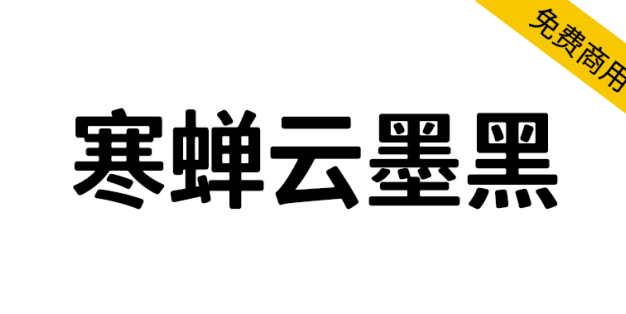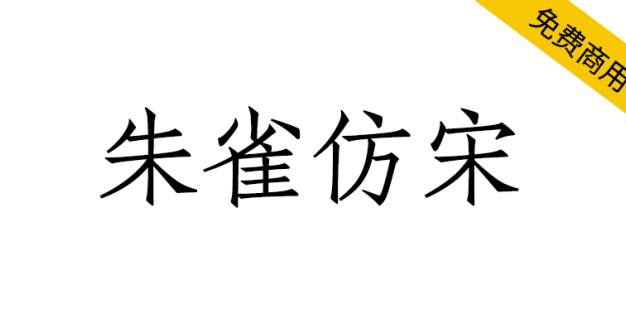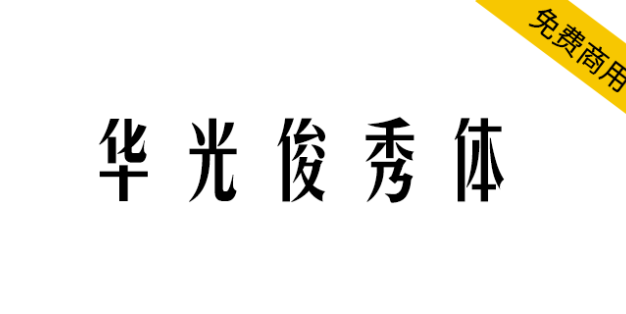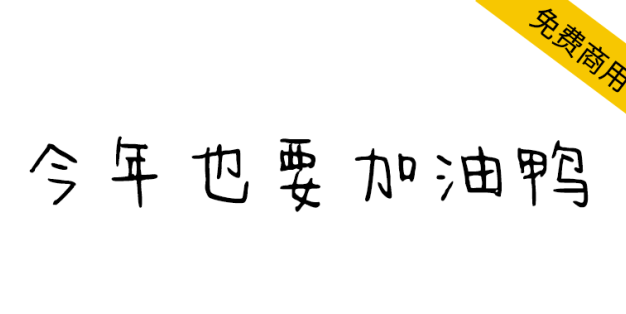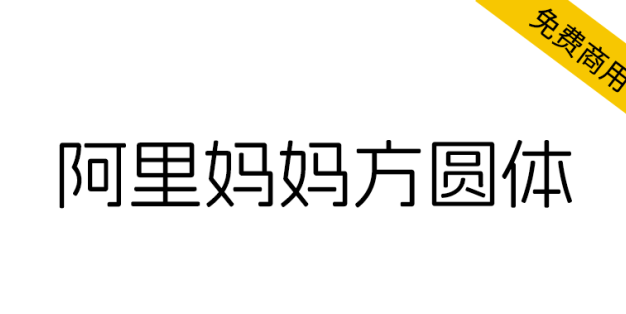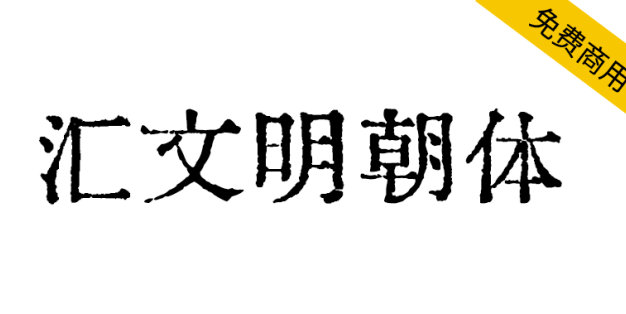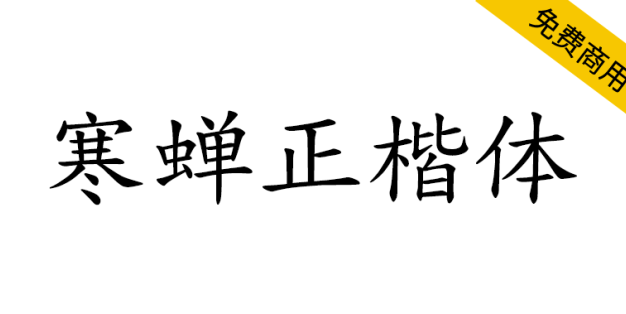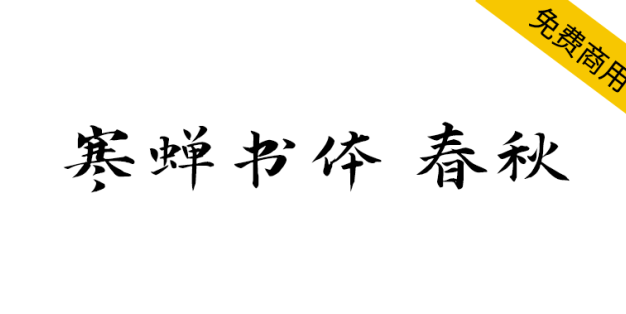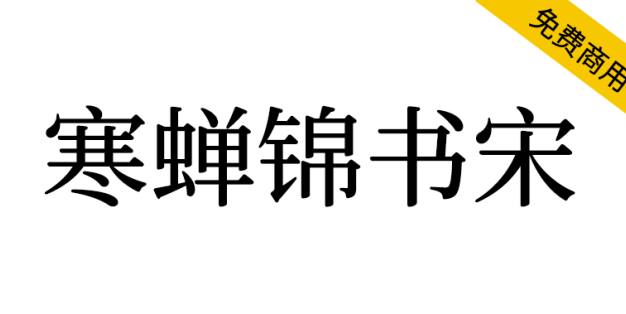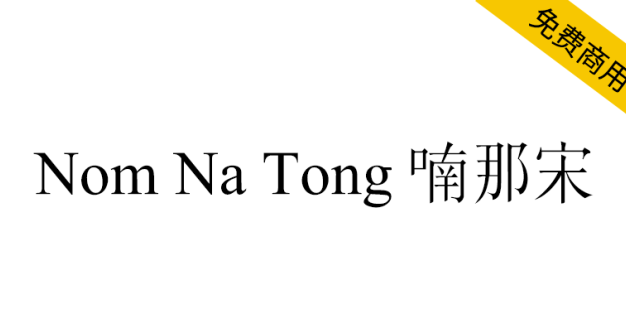
【阿里妈妈东方大楷】还原书法书写韵味,饱满、圆融、浑厚
阿里妈妈东方大楷是基于颜真卿的多宝塔碑算法生成并结合人力完成的一套字库,机器学习到了颜体的丰腴厚重之感,在笔画的描摹上做到了传统书法的收放起伏,规范了骨架、笔画,还原了书法中的落笔、转笔、藏锋、护尾等书写韵味,使整体更饱满、圆融、浑厚。 阿里妈妈东方大楷为中文简体字库,收纳的中文字符包括但不限于GB2312,共计6763个汉字;英文大小写(含全角、半角、合体字等)共105个;常用标点符号共175个…- 0
【阿里巴巴普惠体】面向全社会永久免费商用!
阿里巴巴普惠体是一套全球永久免费正版商用的字体家族,目前涵盖178个语种。阿里巴巴普惠体是一款由中国企业首次发布的可面向全场景使用的免费商用正文字体。以「普惠」之名诞生,阿里巴巴普惠体开放商业授权给所有个人和商家,让更多用户可以免费使用这款字体,以普惠设计助力商业生态增长。 阿里巴巴普惠体3.0为一套符合新国家标准GB18030-2022的简体中文字符集,包含GB18030-2022强制规范三个实…- 0
【乡立方黑体】以字为媒,绘乡村风情,传品牌温度
我是乡立方黑体,由火石品牌字体团队为乡立方量身定制,以字为媒,绘乡村风情,传品牌温度。 乡立方字体设计团队秉承服务大众的原则,致力于打造一款既实用又广泛适用的字体,希望它能被广泛应用于各行各业,真正做到字体好用,适用面广,实现字体使用便捷、应用场景丰富多样,无论在哪种传播媒介中都能展现出卓越的效果。 乡立方黑体总共囊括了4500个基础常用字,可覆盖日常98%的使用范围,未来,我们将根据实际情况逐步…- 1
【阿里妈妈方圆体】目前国内外为数不多的中文双轴可变字体
阿里妈妈方圆体为一款简体中文双轴可变字体,收纳的中文字符包括但不限于GB2312,共计6763个汉字;英文大小写共52个;常用标点符号共227个,总计7042个字符 设计说明:通过智能 AI 的方式在20天内完成的这款字,是目前国内外为数不多的中文双轴可变字体。方体坚实而硬朗,圆体润泽而柔美;方圆间的切换让方圆体极具适用性,也解放了创意表达的更多可能性。粗细的可变使得设计师具备无限微调的可能,让创…- 0
【胡晓波男神体】永久免费商业使用
【寒蝉书体 春秋】基于“演示春风楷、演示秋鸿楷”的拓展字形
寒蝉书体_春秋是基于开源字体“演示春风楷、演示秋鸿楷”的拓展字形 春风 更新提要 调整西文字符及数字大小更加均衡。 调整部分字符忽高忽低的问题。 调整西文字偶距,优化横向排版。 优化竖向排版。 新增 啰 瞭 舖 三字补全一级规范通用字。 新设计的.notdef,补充一些标点符号。 秋鸿 更新提要 调整西文字符及数字大小更加均衡,去除连笔和文字风格更接近,调整粗细。 调整部分字符忽高忽低的问题。 调…- 0
【思源宋体】思源宋体字体下载,免费商用
思源宋体(Source Han Serif)是Adobe 与 Google 合作开发的最新泛 CJK 字体,它是对应于思源黑体的宋体字体。思源宋体与思源黑体这两种字体是为了响应统一设计的需求,以服务于东亚 15 亿人口。 思源宋体支持四种不同的东亚语言(简体中文、繁体中文、日语和朝鲜语),该字体还包含多个西方字形,支持拉丁语、希腊语和西里尔文脚本,这些字形均来源于 Source Serif。思源宋…- 0
【寒蝉正楷体】一个为优化中西文排版的楷体项目
寒蝉正楷体(Chillkai)是一个为优化中西文排版的楷体项目,由中文字体《全字库正楷体》和西文字体《Gentium》重新整合优化。 全字库正楷体字符非常丰富,还有多语言的支持,成为楷体的优秀范本。但西文部分和中文部分不是特别融合。竖排比横排文字排版更好,个人使用感受。 西文部分Gentium是个人最喜欢的西文字体之一,是我认为和楷体搭配最好的西文字体。无论是与文鼎U楷或者其他楷体,整体比原字体西…- 0
【汇文明朝体】一款比较原滋原味的旧铅字印刷风格字体
本字体制作始于2019年1月份,因一切开始于是我扫描《文汇报》上面的《汉字简化方案草案》,后来又收集、扫描了各种历史文献资料,汇总挑选而形成了这样一款字体,故名「汇文明朝体」。 本字体的字形来源主体为五六十年代官方各种汉字改革文件,简体字部分基本复原汉字简化后、字形改造前的书籍印刷体样貌。繁体字、传承字部分基本还原民国至共和国初期字形样貌,是比较原滋原味的旧铅字印刷风格。 收录范围及规则 全覆盖大…- 0
【字体圈欣意吉祥宋】一种圆润纤细古风女性化的字体
整套字形视觉感偏瘦高,宽高比例为4:5,尝试过1:1甚至更矮的比例,不够优雅,因为像这种圆润纤细古风女性化的字体,都是比较修长才好看,最后才决定4:5这个近乎完美的比例。这款字风格圆润,比如横画开头及结尾由传统字体的三角尖凸变成较圆润的风格,竖画由三角尖凸也变成圆润无尖凸风格,竖勾撇捺点的笔画同理2021,祝您吉祥! 这套字涵盖国家GB2312编码标准的6763个中文字符,52个英文字符,10个阿…- 0
【鸿蒙 HarmonyOS Sans】一款多语言的无级可变字体
华为鸿蒙字体 (HarmonyOS Sans),华为定制字体,为鸿蒙OS一同上线,于2021年6月发布上线,可以免费商用。设计上聚焦于功能性、普适性,是一款多语言的无级可变字体,该字体支持简体中文、繁体中文、拉丁、西里尔、希腊、阿拉伯等5大书写系统,105种语言全球化覆盖。 通过研究用户在不同场景下对多终端设备的阅读反馈,综合考量不同设备的尺寸、使用场景等因素,同时也考虑用户使用设备时因视距、视角…- 0
【韩契在民体 한글재민체】基于韩国古文字的字体设计
韩契在民体(韩文名:한글재민체,英文名:hangeul jaemin)是以1908年颁布的《大韩国会开幕原则书》(国家注册文化财第449号)中的毛笔书法字体为基础,由朴载甲前首尔大学医学院教授和金敏国民大学技术设计专门大学院院长共同开发。2020年在韩文字日发布了韩契在民体1.0,2021年增加了KS标准汉字的韩契在民体2.0,2022年又增加了韩国独有的203个汉字和大法院人名用8289个汉字等…- 0
【寒蝉云墨黑】基于思源黑体,添加圆角,更加温润的黑体
基于思源黑体(SourceHanSansSC) 修改,添加圆角,更加温润的黑体。排版细节优化,重构字重比例。 字体风格 使用许可 本字体以SIL Open Font License 1.1(SIL 开源字型授权版本1.1,简称SIL OFL 或OFL)授权协议发布,这个授权的自由度非常高: ✔ 这款字体无论是个人还是企业都可以自由免费商用,也无需知会或者标明原作者。 ✔ 这款字体可以自由传播、分享…- 0
【玄冬楷书】基于开源字体《马善政毛笔楷书》的拓展字体
玄冬楷书是基于开源字体《马善政毛笔楷书》的拓展字体。在原版的基础之上修复了错误的字形并添加竖排排版的特性。 修复以下88字:井僖凳厨商啥堀墒夂娈媵嫌将尴崞嶝庐彀德忒愦揆搛晰暇睽曦歧淀淦潸澄澧濑灸熵燕犟瓢瘗瘪癞癸登 皙眍睽瞟瞧瞪硭磴礁票禽窄窿篥籁羲腼舞雩萼葵蒋蒹螵觳诨谯赖赝蹰辔酹镍镘镞镪镫阕隹饧饰鸢鹉鹧。 调整都分汉字字面的问题。增加 vert 特性,用于竖向排版。新增“啰瞭”二字,补全一级通用规范…- 0
【朱雀仿宋】璇玑造字的开源仿宋字体计划
「朱雀仿宋」是璇玑造字的开源仿宋字体计划,志在最终提供高质量的、支持多语言的正文仿宋解决方案。 仿宋作为「宋黑仿楷」中文四大基础字体之一,长期缺乏开源许可证下的选择。我们希望「朱雀仿宋」可以弥补这一空缺,为开源软件与 TeX 社区贡献一份力。 上世纪初,仿宋活字一度品类繁盛,开发、应用风行一时。然而时过境迁,市面上的仿宋最终收敛于「华丰真宋」一系,这也是今天大多数人所熟悉的仿宋样貌。「朱雀仿宋」则…- 0
【寒蝉锦书宋】基于思源宋体,添加圆角,更加温润的宋体
寒蝉锦书宋(ChillJinshuSong)基于思源宋体(SourceHanSerif)修改,添加圆角,更加温润的宋体,排版细节优化,重构字重比例,字体粗细更加均衡,便于阅读。名为锦书体,既是锦上添花,又是前程似锦之意。 字体风格 使用许可 本字体以SIL Open Font License 1.1(SIL 开源字型授权版本1.1,简称SIL OFL 或OFL)授权协议发布,这个授权的自由度非常高…- 0
【Nom Na Tong 喃那宋】越南Nôm保护基金会开发的字体
这是“Nom Na Tong”字体的存储库。Nom Na Tong字体最初是在越南Nôm保护基金会的赞助下开发的http://www.nomfoundation.org,成立于1999年。该字体的开发既是以Unicode编码越南Hán-nôm文字的建议的最终来源,也是促进使用该文字书写的作品遗产的途径。该字体目前包含26000多个字形,代表了学者、软件工程师和其他专家的集体工作。它仍然是正在进行的…- 0
【黄令东齐伋体】一款可以媲美康熙字典体的免费商用字体
黄令东齐伋体(QIJIFALLBACK),一款可以媲美康熙字典体的免费商用字体,摘自明代木版印刷书籍《凌閔刻本》,采用半自动计算机视觉和OCR制作而成的一款字体。基本思源宋体改造而来,对中文汉字支持极佳,无论是简体还是繁体都基本上不缺字! 字体风格 黄令东齐伋体,笔画风格书法特征浓郁,比常规的明朝体更具韵律感,富有人文气息。黄令东齐伋体非常适宜用于需要展现人文感、手作感、古拙感的场景。 使用许可 …- 0
【方正书宋】方正免费字体,杂志书籍正文首选字体
方正书宋源自上海印刷技术研究所的宋二,原字形距今已有近60年。最初的设计就是专门针对最常用的小字号正文排版。方正书宋的字形端正清秀,中宫适度。凭着清晰爽目、久读不易疲劳、印刷适性好的优点,长期被作为杂志和书籍的正文首选字体,所以也是一款非常经典的正文宋体。 字体风格 方正书宋的字形端正清秀,中宫适度。凭着清晰爽目、久读不易疲劳、印刷适性好的优点,长期被作为杂志和书籍的正文首选字体 使用许可 方正书…- 0
【黄令东齐伋复刻体】十分漂亮的古籍字体!
【鸿雷板书简体】一款近乎完美的手写字体,如约而至
作为一个书写爱好者,也作为一个设计从业者,或许都会想着有属于自己的一套字库。 去年中旬开始了解字库后边愈发的想要完成这么一件,哪怕不是那么完美,也很想拥有一套自己的字体。 ----------------------------------------- 字数:>6800 简繁:简体 命名:鸿雷手书简体 书写:我 封装:我 排版:我 -----------------------------…- 0